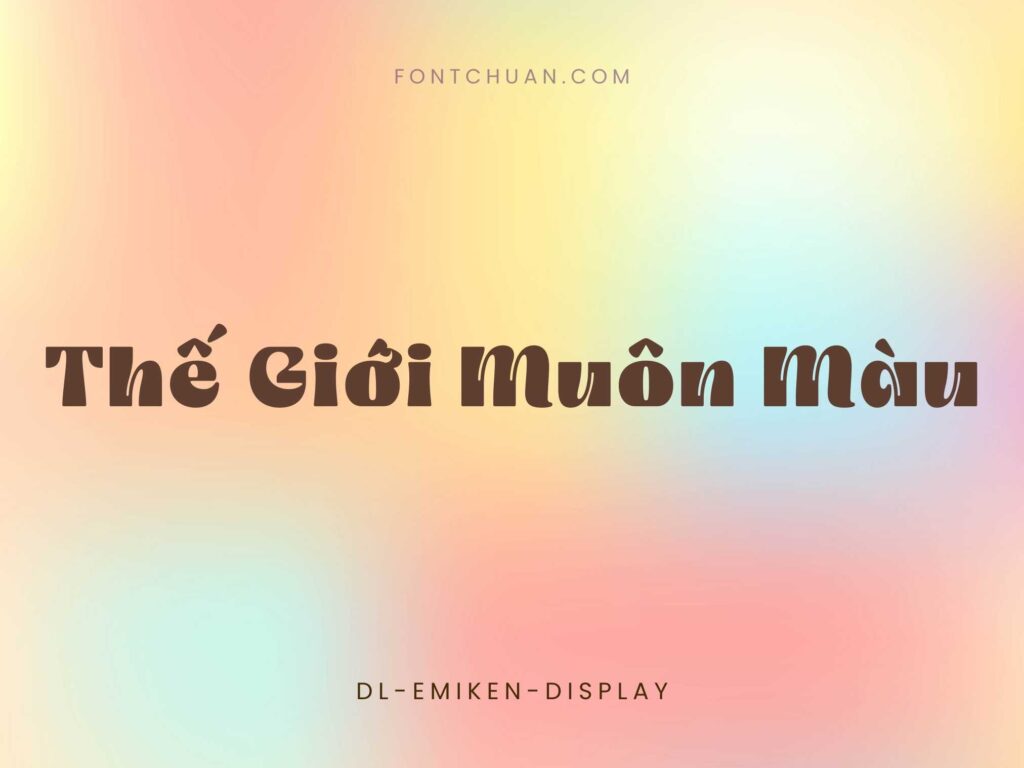
Font DL Emiken Display Việt Hóa
Tác giả Font: Attract Studio
Việt hóa bởi: Tduy
Emiken Display là một font chữ mang phong cách độc đáo, nổi bật với thiết kế hiện đại nhưng vẫn giữ được nét cổ điển đặc trưng. Font này được sáng tạo bởi Attract Studio vào năm 2022, mang đến một diện mạo mạnh mẽ, thu hút và phù hợp với nhiều loại thiết kế khác nhau. Nhờ sự hỗ trợ của FontTiengViet, phiên bản Việt hóa của Emiken Display đã được tối ưu hóa để hiển thị đẹp mắt với tiếng Việt, đồng thời hỗ trợ hơn 50 ngôn ngữ khác trên toàn cầu. Thành viên của Font Chuẩn đã sưu tầm và chia sẻ font này để đáp ứng nhu cầu đa dạng của người dùng trong các dự án sáng tạo.
Về thiết kế, Emiken Display có cấu trúc chữ dày dặn, bo tròn nhưng vẫn giữ được độ sắc nét, tạo cảm giác cân đối và thẩm mỹ cao. Các ký tự được thiết kế với độ tương phản rõ ràng, giúp font dễ đọc và nổi bật trên nhiều nền tảng. Nhờ vào các ligatures và ký tự thay thế phong phú, Emiken Display mang đến sự linh hoạt tối đa cho các nhà thiết kế. Font này đặc biệt phù hợp để sử dụng trong các thiết kế logo, tiêu đề, poster, bao bì sản phẩm và branding. Với phong cách nổi bật, Emiken Display thường được ứng dụng trong ngành quảng cáo, thiết kế đồ họa, ấn phẩm sự kiện và thời trang, giúp nâng cao giá trị thẩm mỹ của sản phẩm.